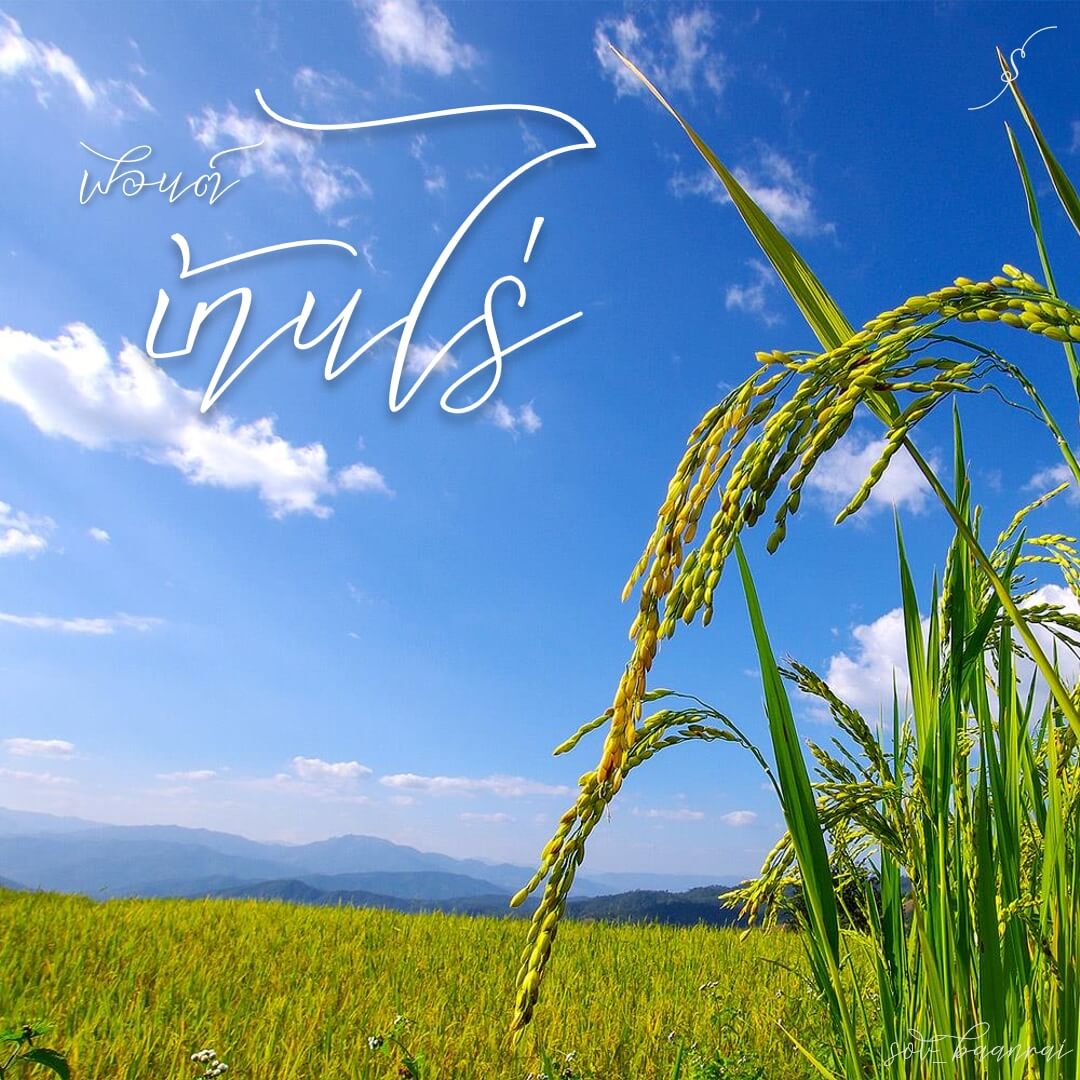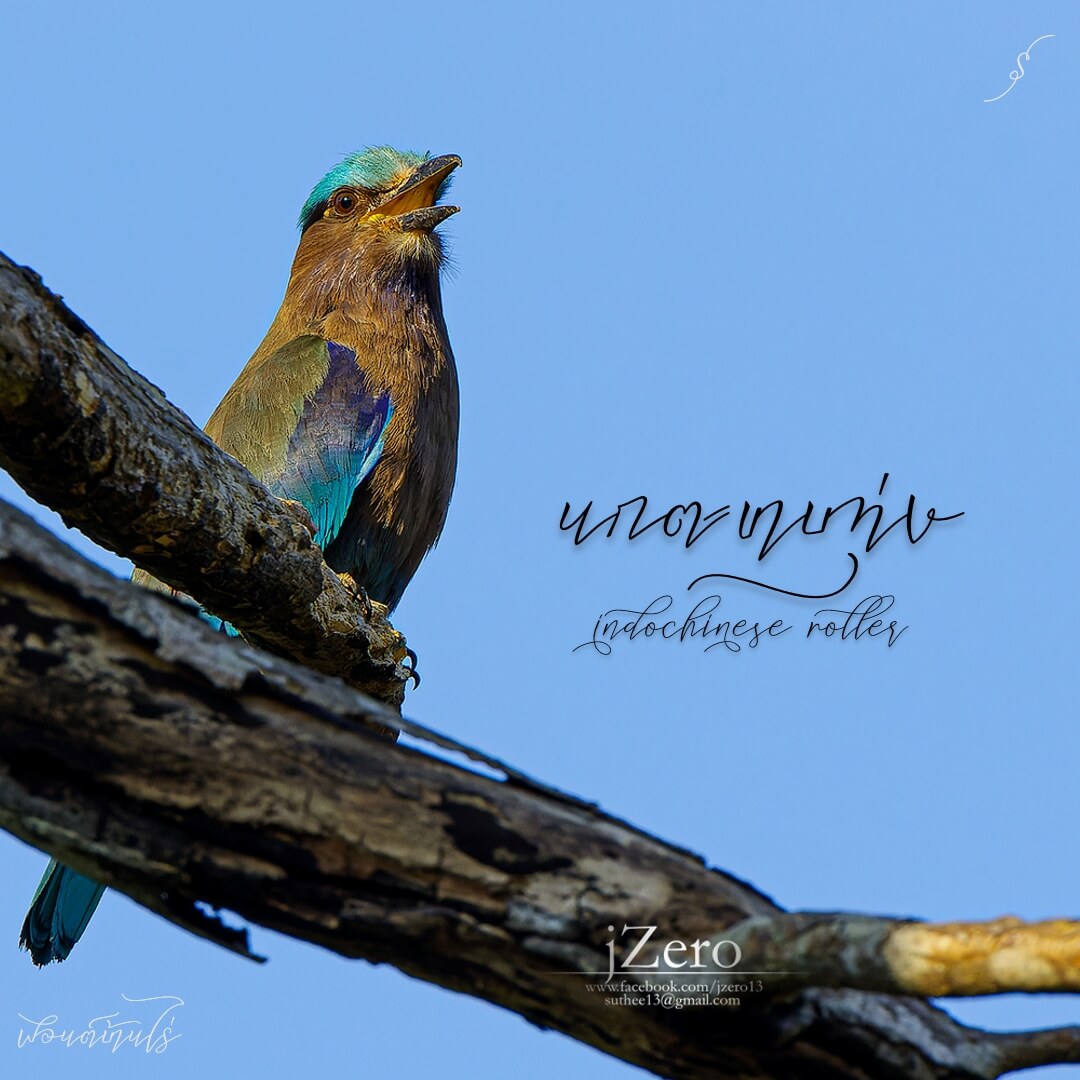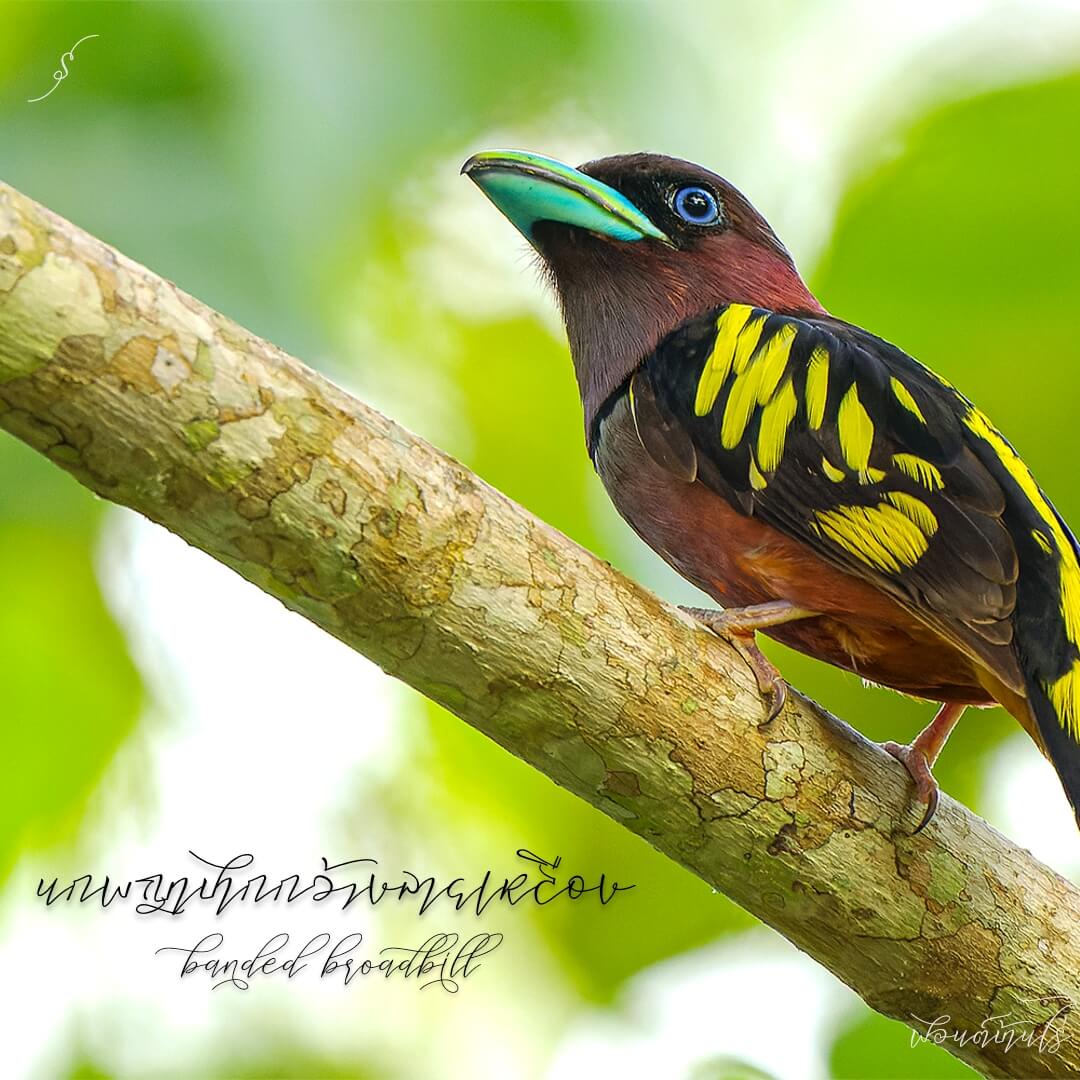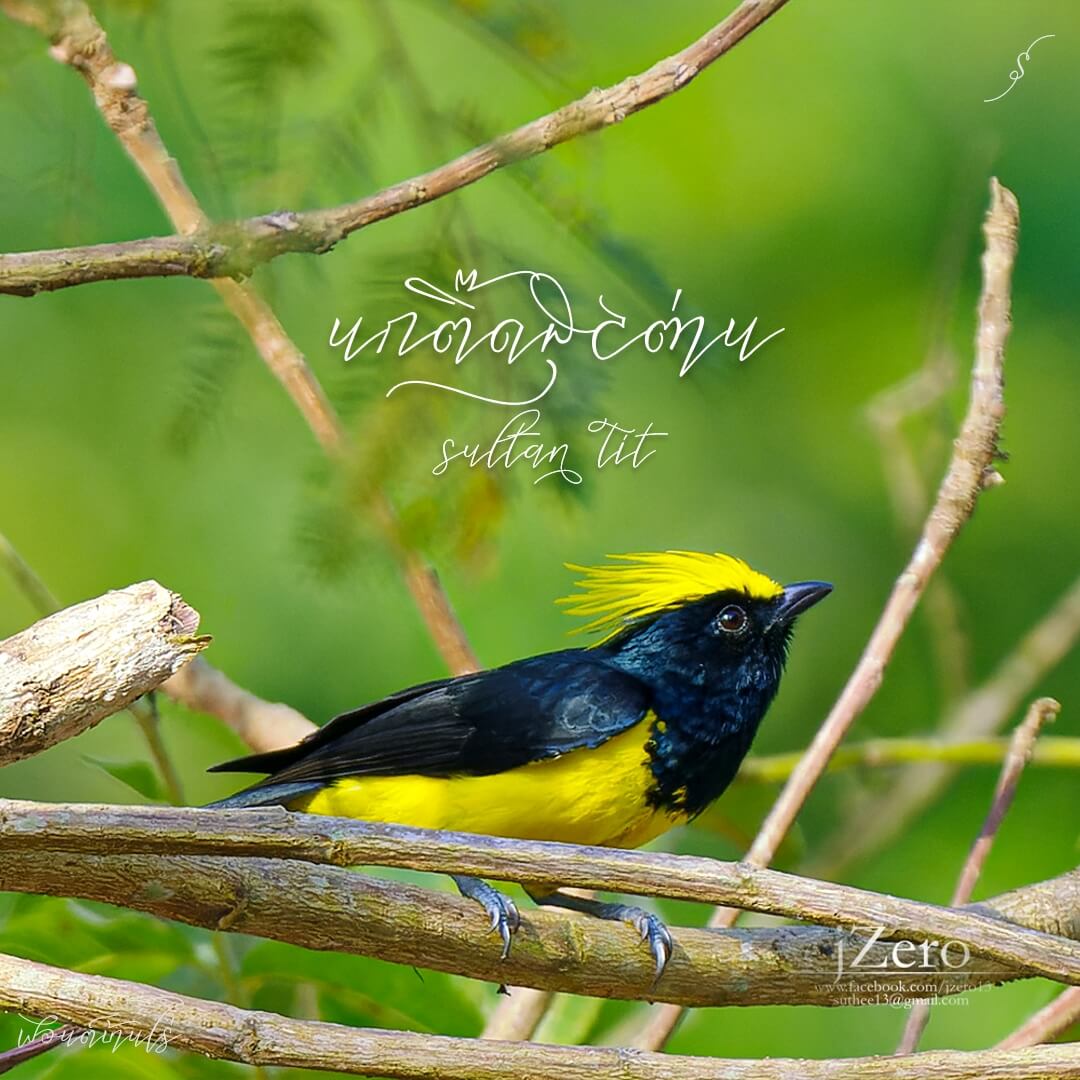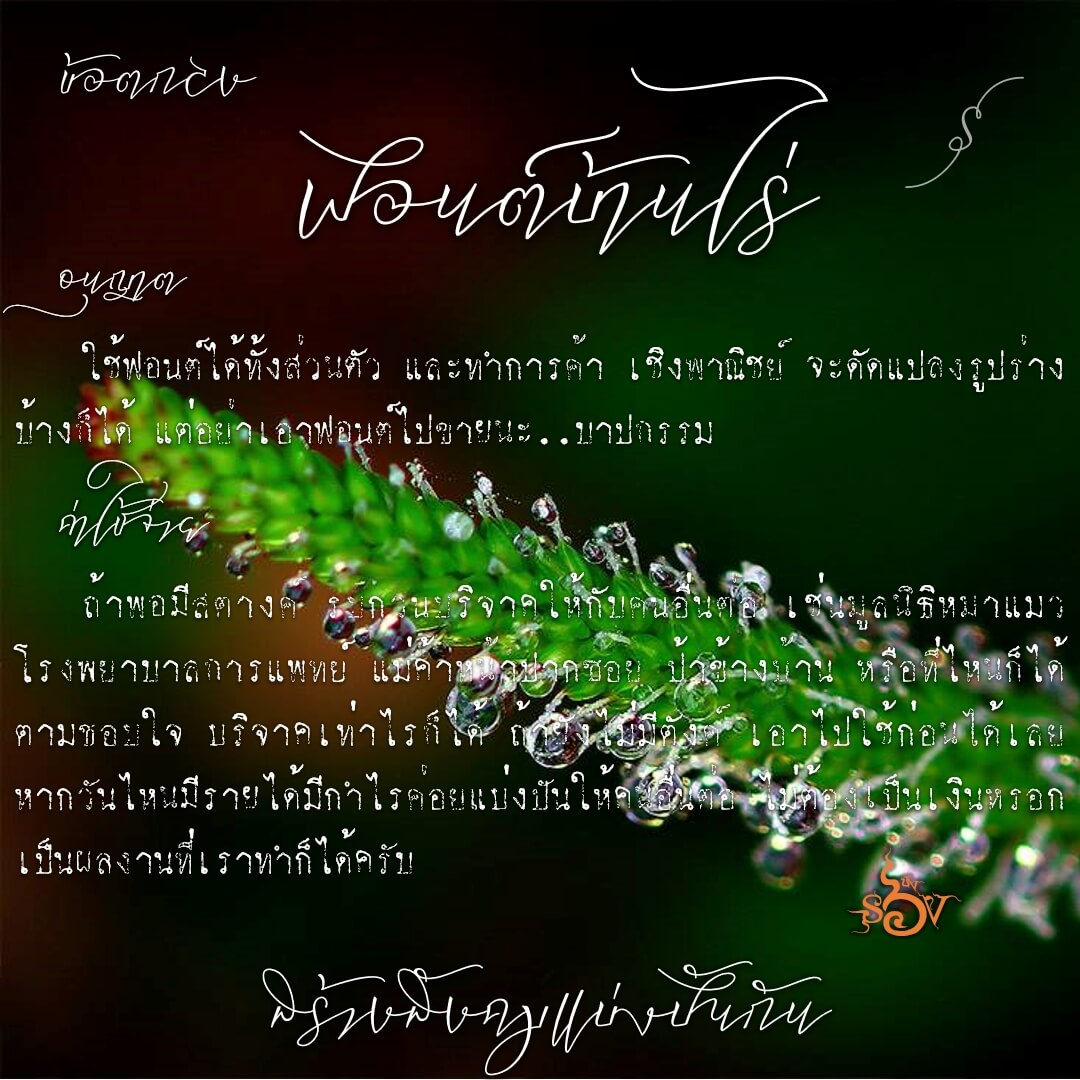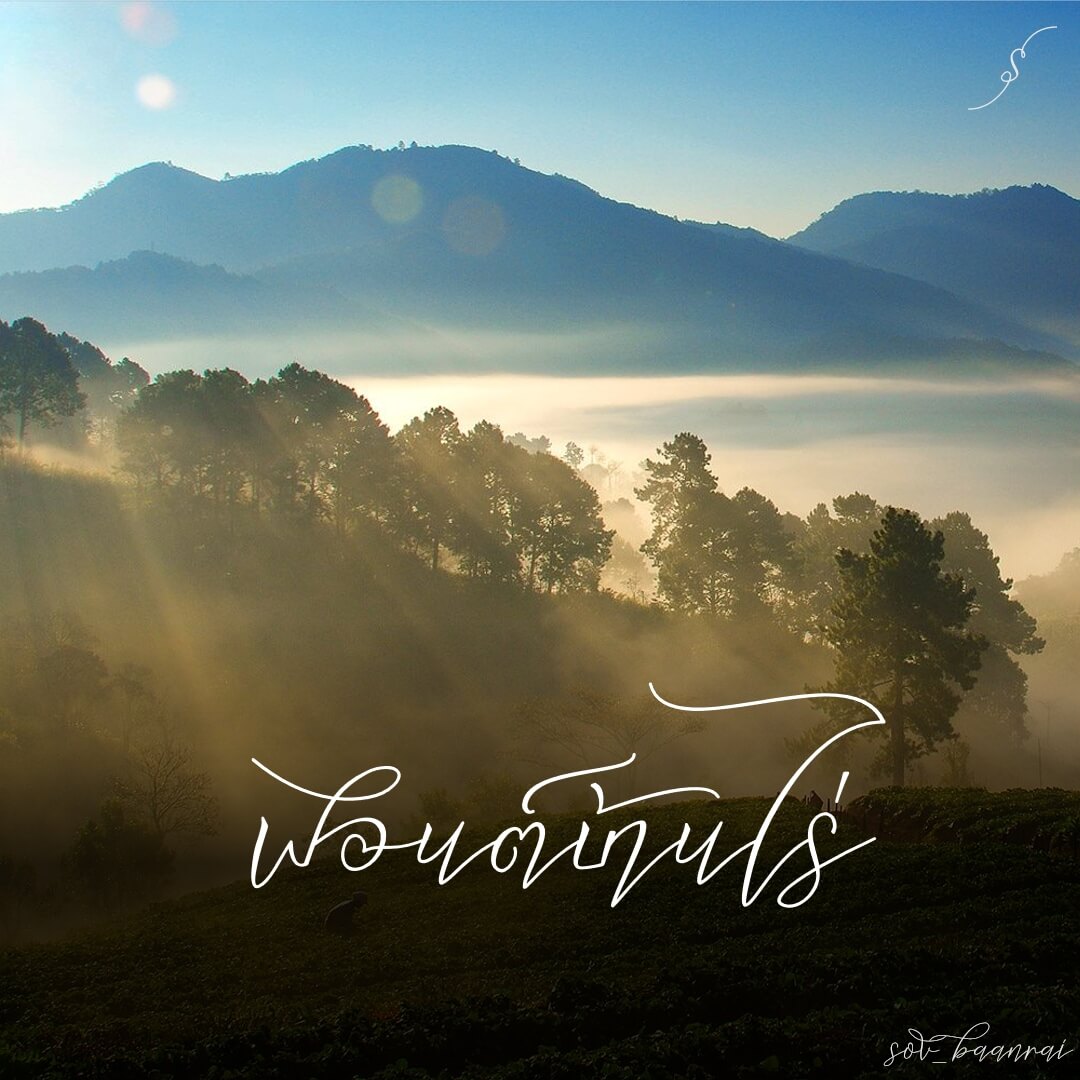
ฟอนต์บ้านไร่ – ลายเส้นปากกา แนว advanced modern calligraphy ภาษาไทย อ่านไม่ง่าย เหมาะใช้ประกอบฟอนต์หลัก หรือวัตถุหลักอื่นๆ
เบื้องหลังการออกแบบ : ฟอนต์ บ้านไร่
บ้านไร่ (SOV_BaanRai)